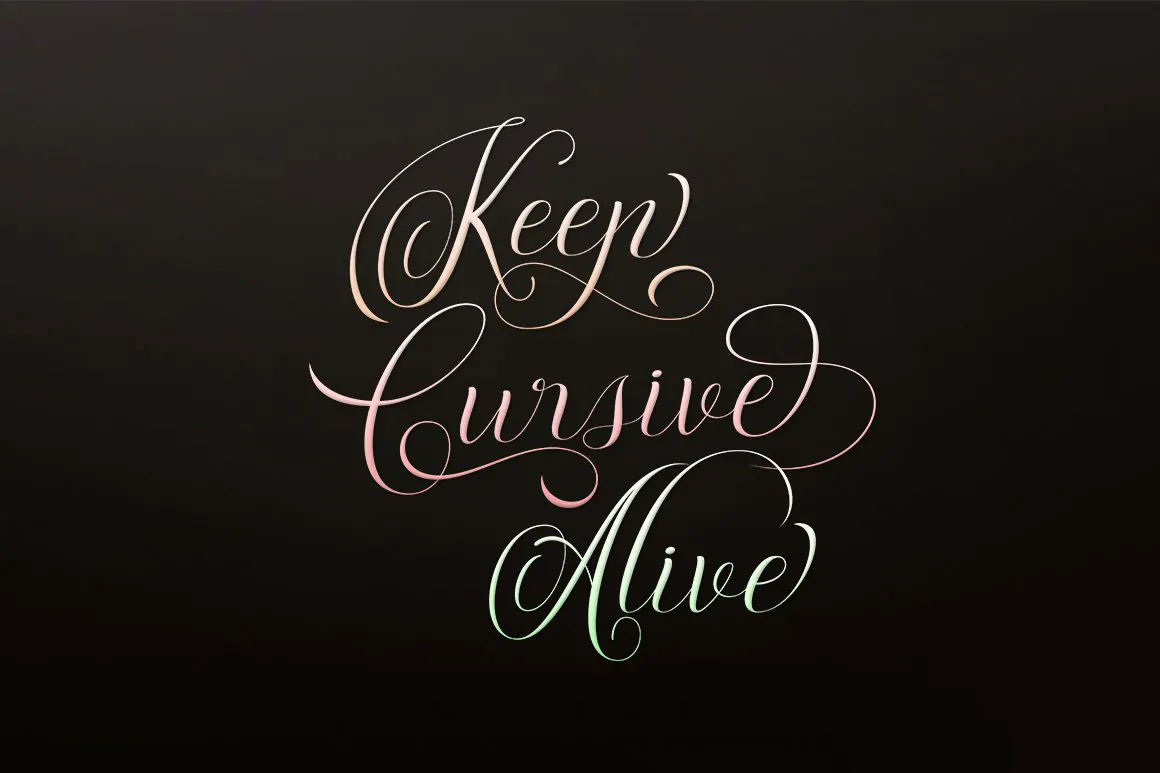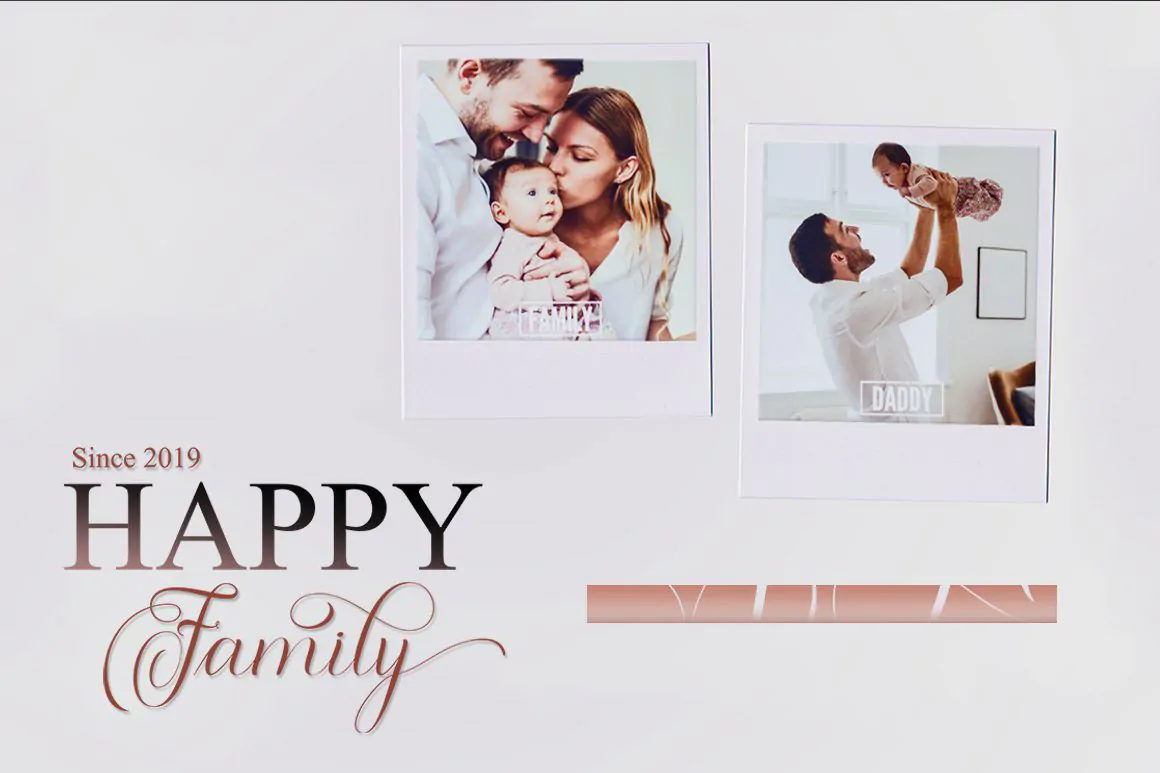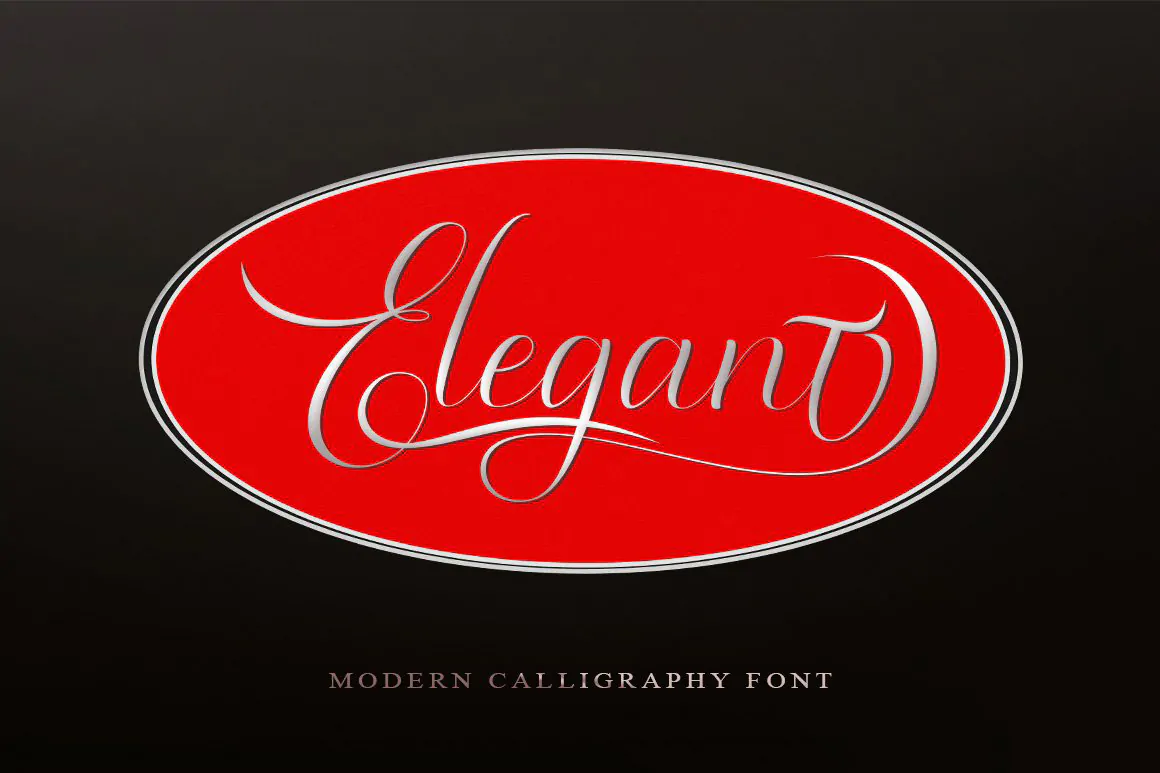
فونت کالیگرافی Moderena
فونت کالیگرافی انگلیسی
فونت کالیگرافی Moderena یک قلم اسکریپت و زیبای انگلیسی است که میتوانید در طراحی انواع پوستر و کارت از آن استفاده کنید. این قلم با سه وزن معمولی، ضخیم و مورب طراحی شده است.